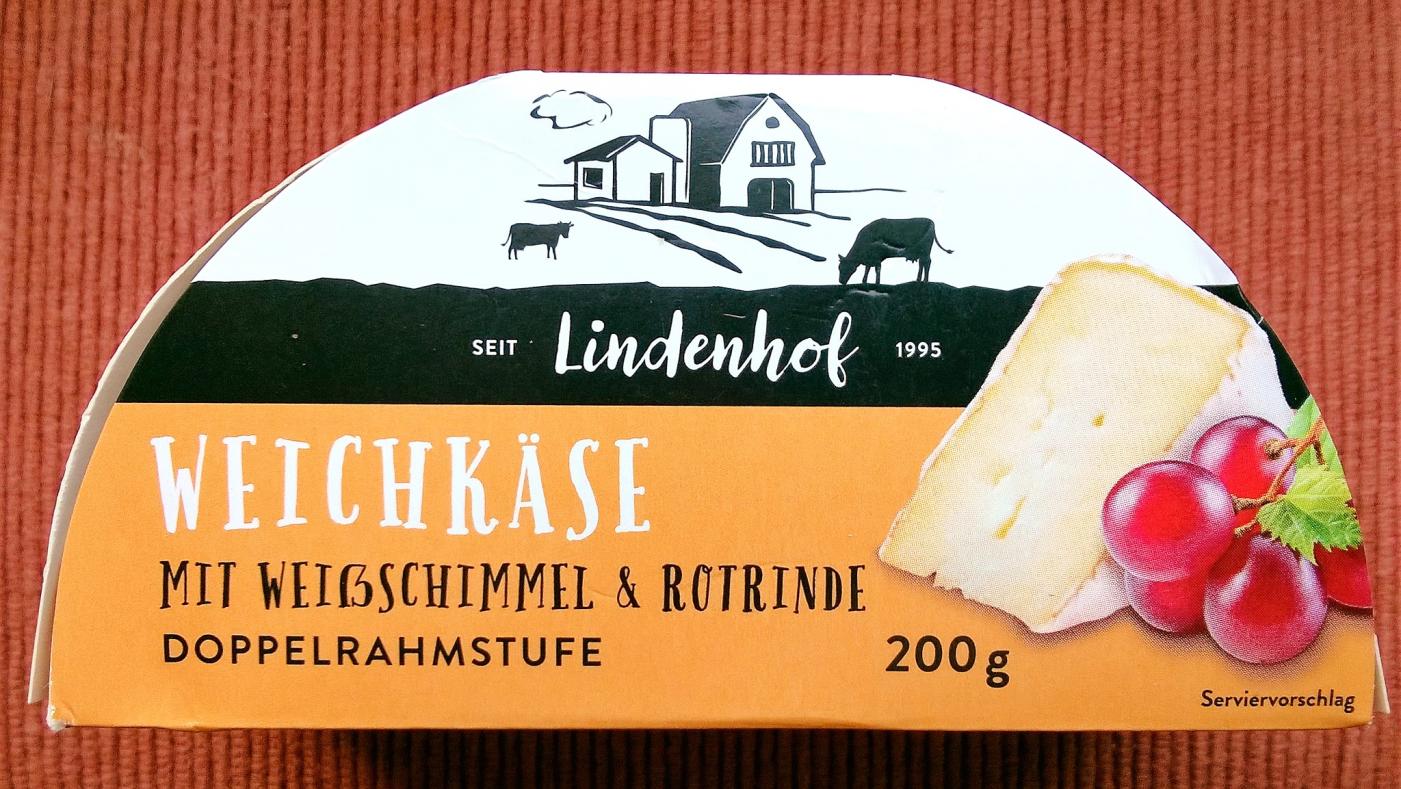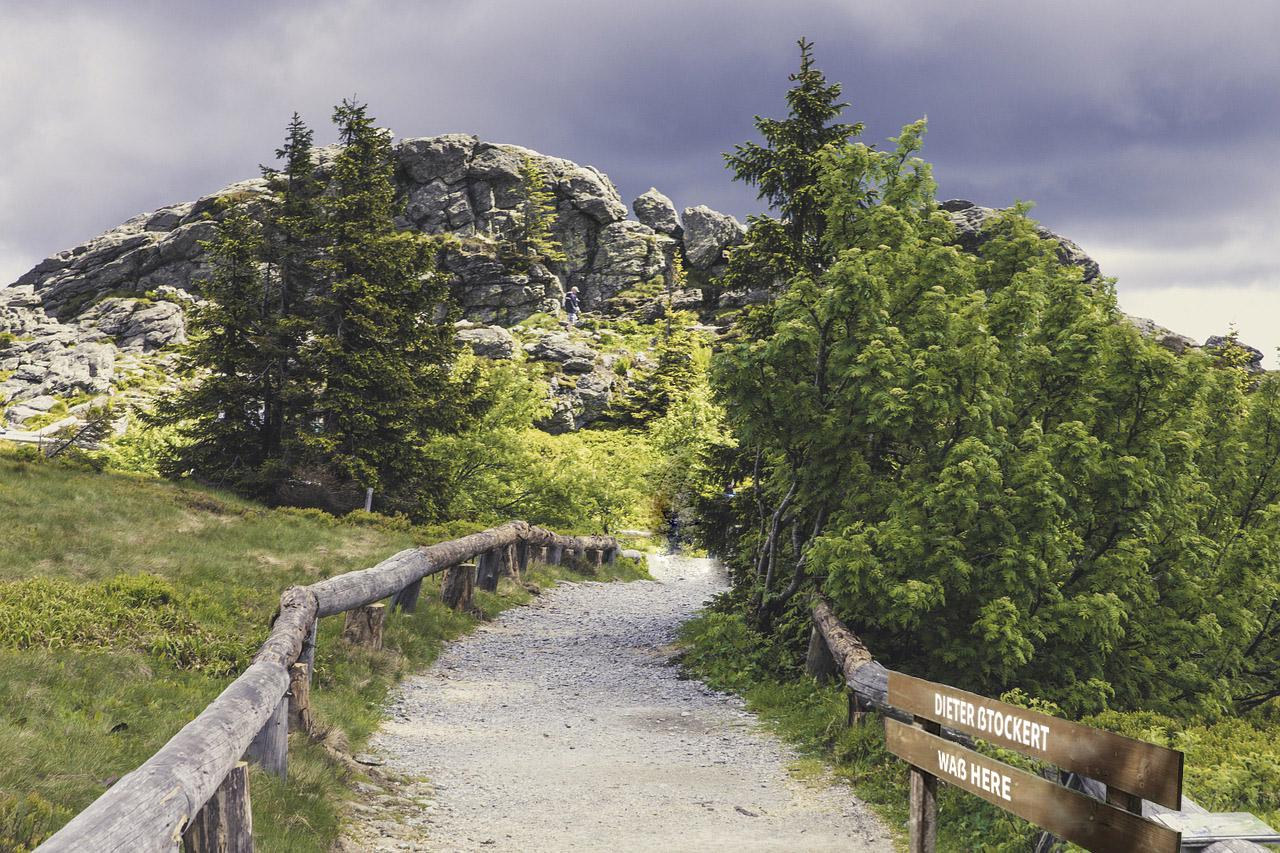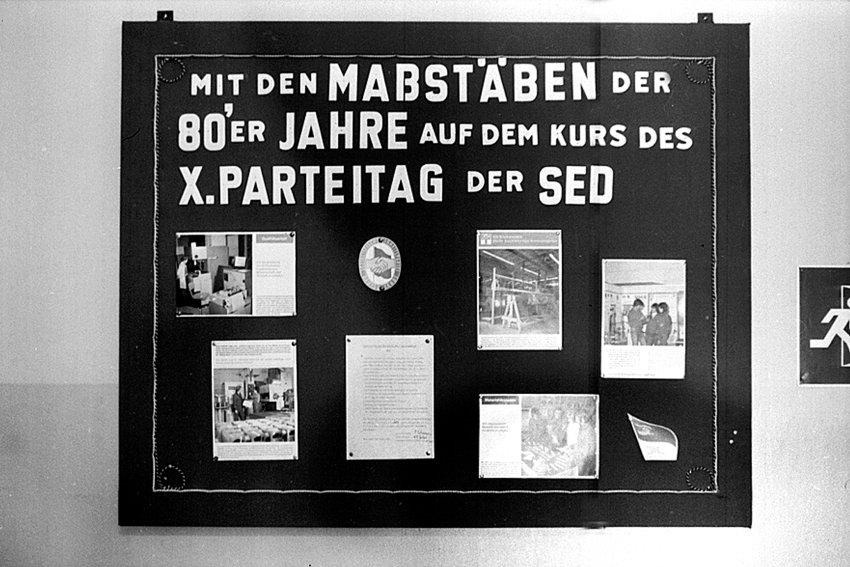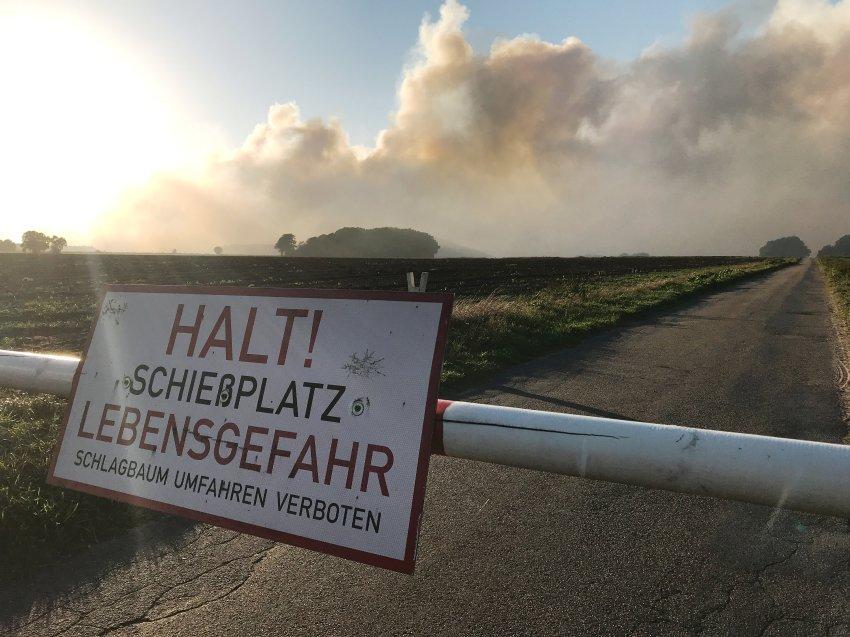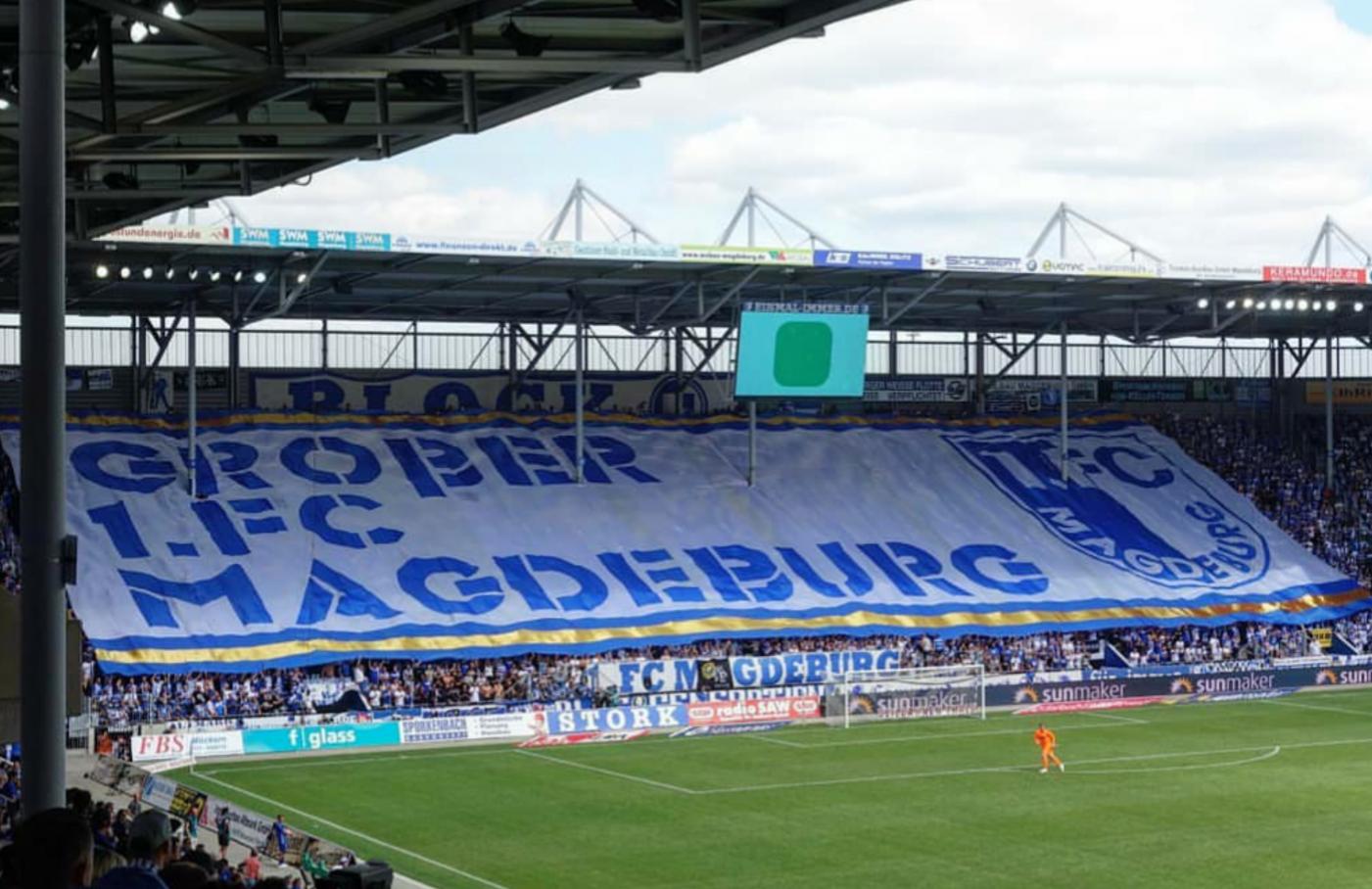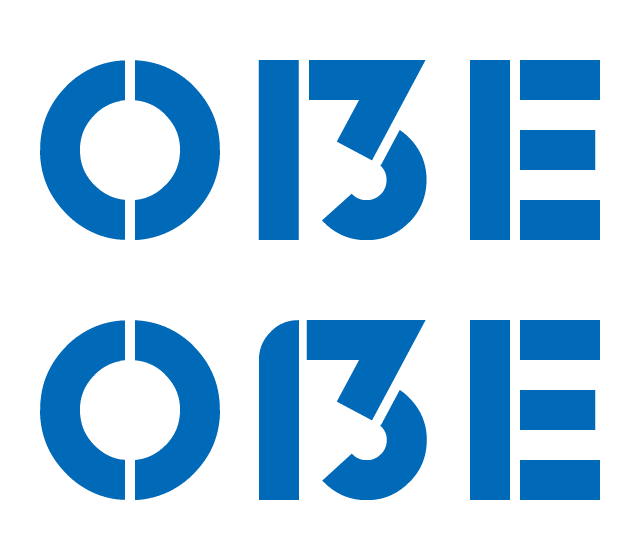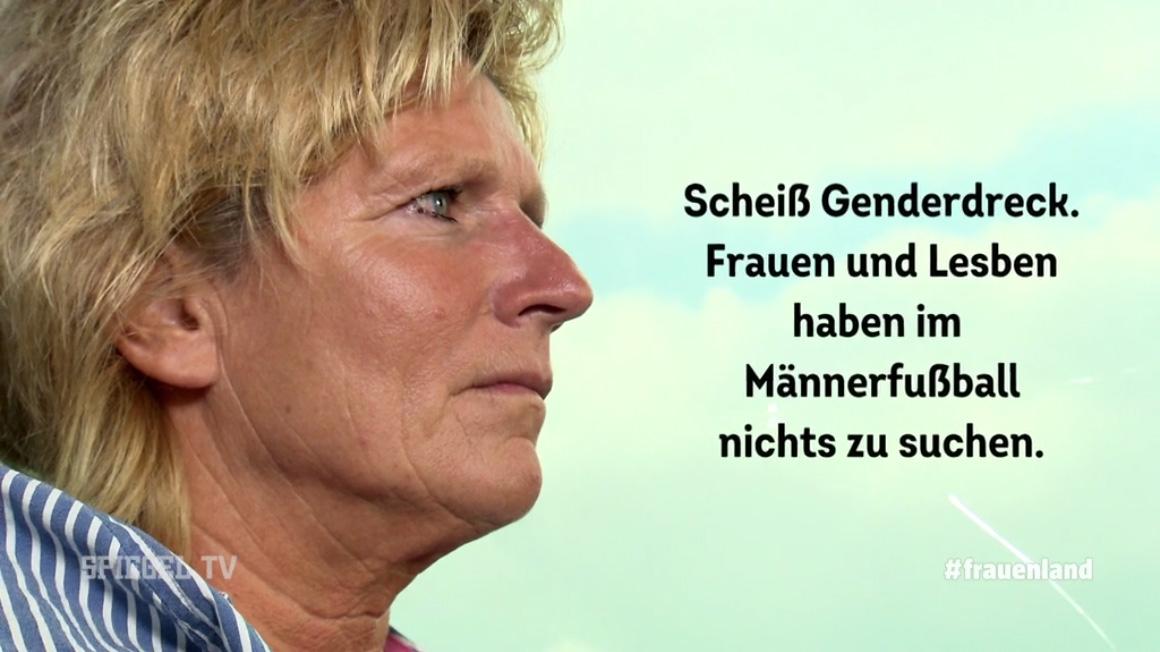
Fußball? FUẞBALL? 🤔 Da mach’ ich doch mal gleich weiter …
Was gibt es nicht für tolle ẞ-Formen: Dresdner, Leipziger, Wolgaster, Zehlendorfer, … und jetzt auch die Machteburjer:
Deren Prinzip: Ist zu nah am B es dran, mach ne Unterlänge ran!
Und nun weiß man auch, wie man das ẞ ersatzweise auf ASCII-Tastaturen schreiben kann/sollte:
das gro13e!
Wie sähe deiner Meinung nach denn eine gelungene Form für ein Versaleszett im Stil dieser Schablonenschrift aus?
Ohne vorherige Recherche habe ich gerade einen (schnell auf Raster konsturierten) Versuch gewagt:
Kann man aber trotzdem als 13 lesen, wenn man unbedingt will.
Eine 13 sehe ich in beiden Fällen nicht. Ich denke da kommt es auf die Buchstabenabstände und die Stege an und, dass der Unterschied deutlich erkennbar ist. Das ist m. E. hier gegeben.
Aber die Nähe zum B ist mir im Foto tatsächlich zu eng. Aber vielleicht sind das ja auch eher die Jungs fürs Grobe ... :-?:hammer:
Damit kein Missverständnis entsteht: ich finde es ja überhaupt schön, dass sie das ẞ benutzen (bzw. sich an der Gestaltung eines solchen versuchen). Solange das keiner macht (aus Angst, es falsch zu machen), wird das nie was mit der Normalisierung des ẞ. Und selbst in der Form wie oben finde ich es also Welten besser als SS. Das wird schon!
Was die Vermeidung des 13-Eindrucks angeht, der mir in Christians oberem (ansonsten sehr gelungenem) Entwurf besonders ins Auge springt, liegt das wohl vor allem an den Stegen. Ich würde den oberen einfach von der linken zur rechten oberen Ecke verschieben (und dort schräg stellen), das sollte die Wirkung eines Buchstabens verstärken.
Letzte Nacht habe ich vom Versal-Eszett geträumt.
Wen es interessiert: Wir waren Wandern in einer bergigen Landschaft, die ich als Bayerischen Wald angesehen habe, mit gleichzeitigem Anklang an die Dolomiten. Und irgendwo im Tal hing ein Hinweisschild, von dem ich nicht mehr weiß, was draufstand, nur dass die Beschriftung zweizeilig war und in der ersten Zeile ein Versal-Eszett enthielt. Die Buchstaben waren nicht handgemalt, sondern gedruckt, aber es sah so aus, als wäre jedes Zeichen auf Stoff gedruckt und einzeln aufgeklebt, ein paar Buchstaben waren auch nicht mehr richtig fest.
Sogar die Bundeswehr hat mitbekommen, dass SS heute nicht mehr zeitgemäß ist. Das ß muss zwar erst noch erwachsen werden, aber das wird schon …
Ansonsten wäre ich übrigens dafür, der deutschen Sprache ganz offiziell noch ein paar optionale bedeutungsunterscheidende Diakritika zu spendieren, damit ich unmissverständlich weiß, ob hier nur das Ụmfahren des Schlagbaums verboten ist oder auch das Umfạhren.
Glücklicherweise war aber das Fahrzeug mit einer modifizierten Lichtmaschine ausgestattet, aus der man 220V bis 2kW ziehen konnte, aber die auch sie als Schweißgenerator bis 3,5mm Elektroden sich umschalten ließ
Und als ich dort an kam, hatten die Kollegen längst Feierabend und die Schranke war zu.  Da der Zaun des Geländes recht massiv war, ebenso die Pfosten der Schranke, war weder umfahren noch umfahren eine Option. Zumindest hätte ich wohl Ärger wegen der massiven Beulen im Firmenauto bekommen.
Also den Winkelschleifer aus dem Kofferraum, den Schloss-Riegel vom Pfosten getrennt, aufs Gelände gefahren, Schlossriegel wieder fest gebrutzelt, etwas abkühlen lassen, Zink-Spray (war auch im Kofferraum :-) ) über die neue Schweißnaht und ab ins Bett.
Meine Kollegen haben sich am nächsten Morgen sehr gewundert, wie ich da aufs Gelände gekommen bin, hatten sie doch grad erst ein neues Schloss an die Schranke gebaut, und den Schlüssel hatte in der Firmenzentrale noch niemand...
vor 2 Stunden schrieb R::bert:
Obwohl der i-Punkt selbst mir als Typo-Laie irgendwie falsch vorkommt ... etwas zu weit rechts platziert‽  ;-)
Hier wäre ich wohl möglich auf die Beschriftung so abgefahren, dass ich jetzt diesen Weichkäse auf dem Brot hätte :-)
Edit: HUCH, ich hab den sogar!!! War vorgestern in einem Schadenspartienmarkt *), und hab es gar nicht so richtig mitbekommen, was für Marken ich da mit nahm... Na so was!!!
Abgesehen davon, dass ein großes Eszett vollkommen natürlich ist, wäre die alte Schreibweise bei dieser Schrift eine gestalterische Katastrophe. Ich behaupte, dass diese Schrift nur deshalb zur Anwendung kommen konnte, weil sie ein großes Eszett zur Verfügung stellt.
DDR-Wandzeitung, 1981:
Man sieht mal wieder, wir Ossis waren (notgedrungen) erfinderisch. Ein B, zwei beherzte Schnitte, schon haste das ẞ.